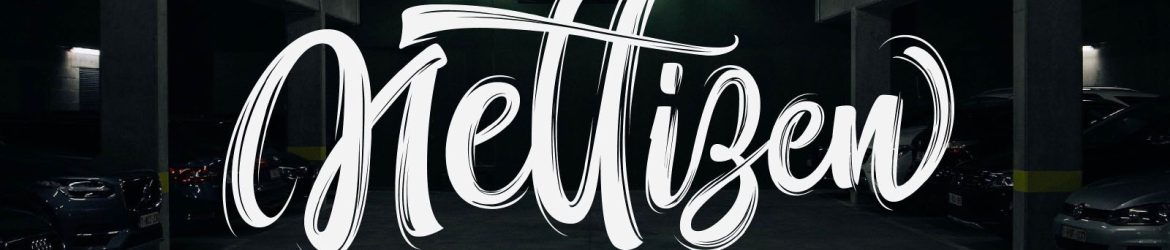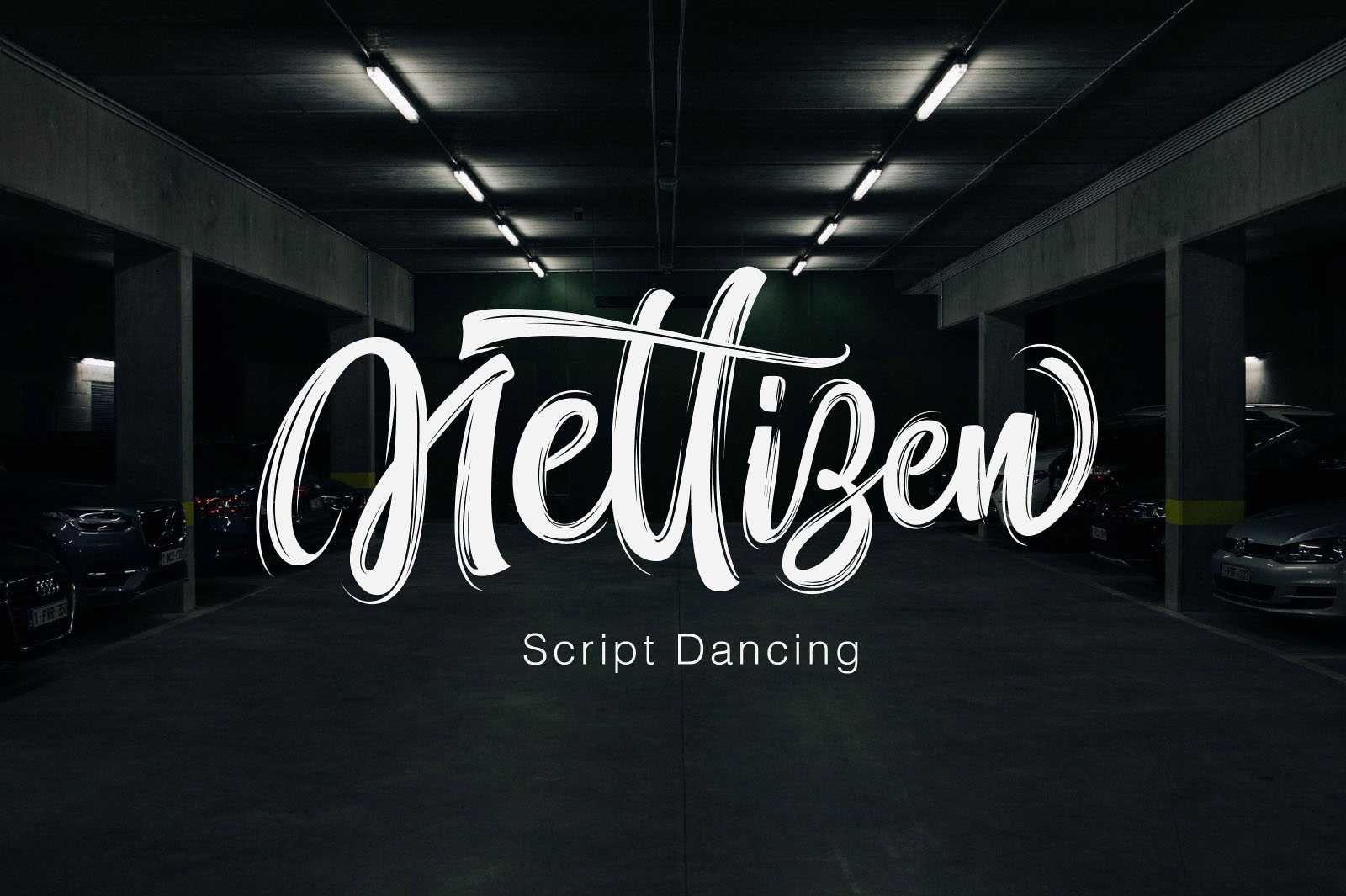
Nettizen Script Dancing Font
A Nettizen Script Dancing é uma fonte contemporânea e atraente que traz vida a qualquer design. Esta fonte é ideal para uma variedade de projetos, desde convites de casamento e materiais de marca até logotipos, camisetas e cartazes. Suas formas elegantes e sua escrita em movimento tornam seu trabalho mais chamativo e belo. A fonte é um script dançante único que adiciona um toque especial às suas criações. Contém caracteres padrão, letras maiúsculas e minúsculas, números, pontuação e símbolos internacionais. Esse é o recurso perfeito para quem deseja dar vida a seus projetos com um estilo moderno e envolvente.